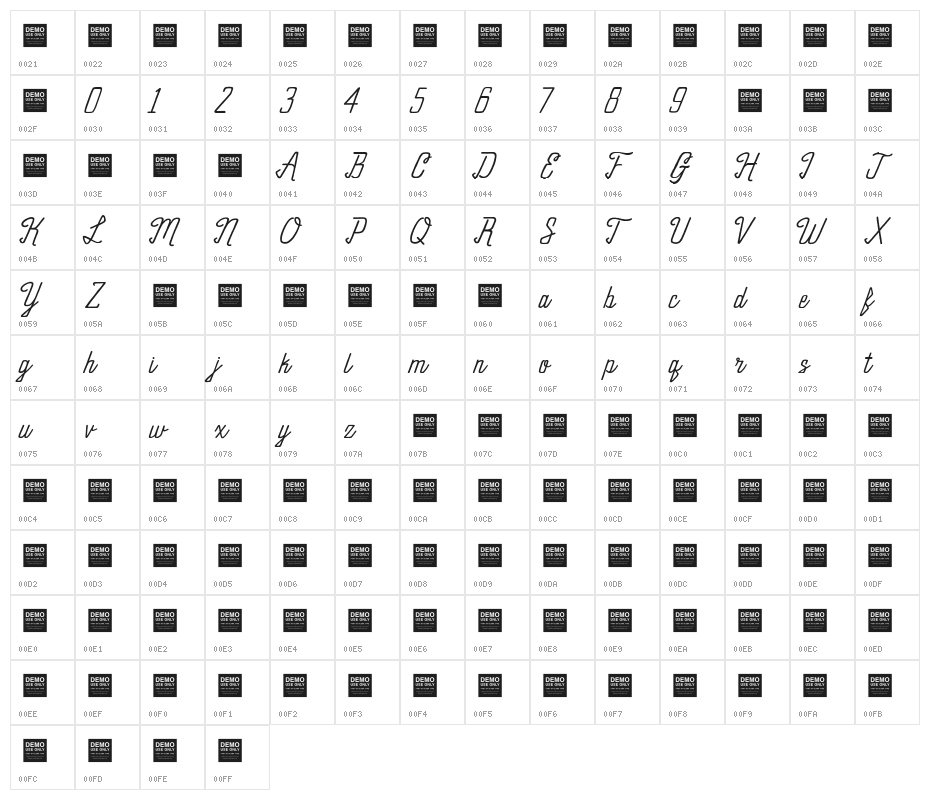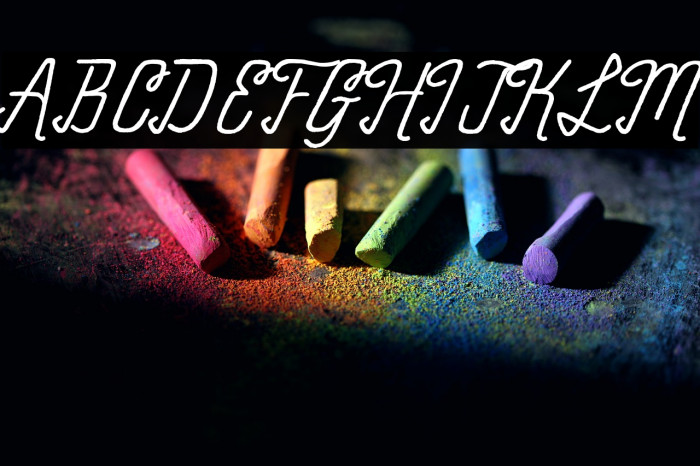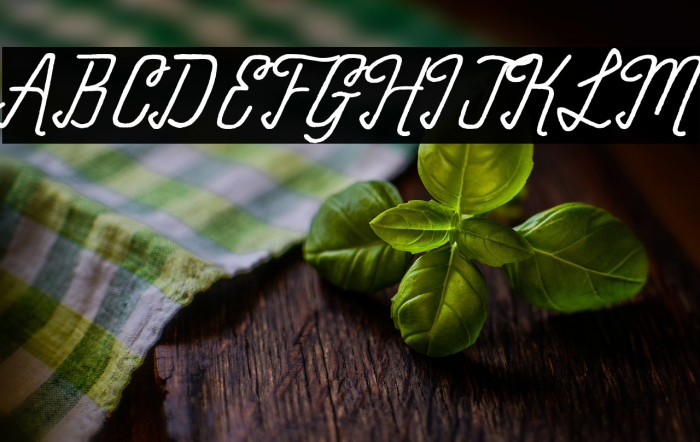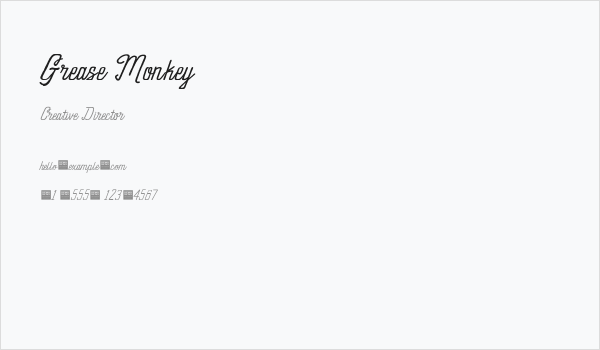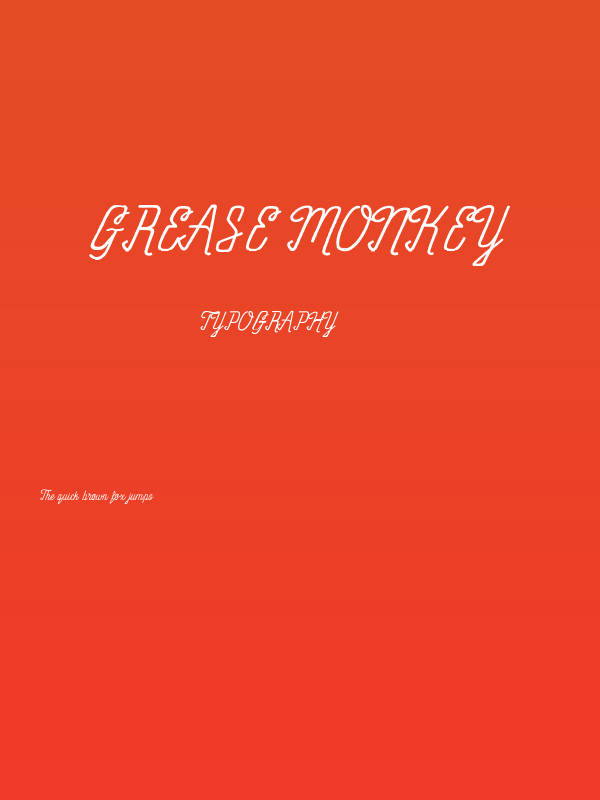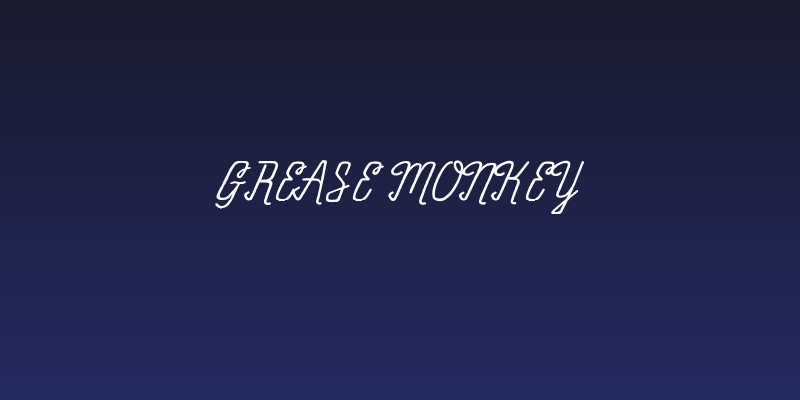
Grease Monkey Font
✎ Script
| الفئات | Script |
| مائل | Yes |
| النمط العام | Vintage |
| حالة الاستخدام | Logos, Invitations, Signage |
| مشاريع مقترحة | Ideal for branding, invitations, signage, and any project that requires a touch of elegance and nostalgia. |